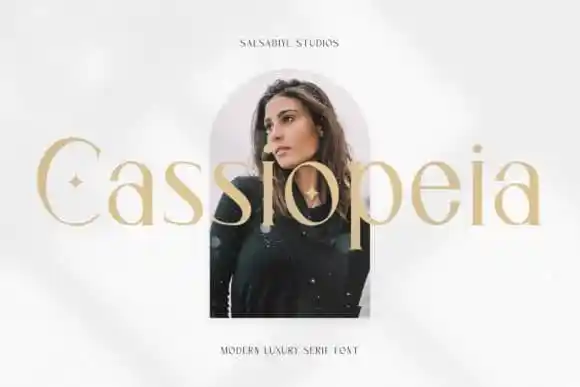
Cassiopeia Serif Font – Download Grátis
A Cassiopeia Serif é uma elegante tipografia serif que traz os benefícios do design moderno, minimalista e moderno ao mesmo tempo. Perfeita para seus projetos de marca pessoal, esta fonte oferece alternativas de caracteres suficientes para atender a um público diversificado. Salsabiylstudios é o criador desta elegante tipografia que abraça o design altamente sofisticado e refinado. Ela se destaca com suporte multilíngue, garantindo facilidade em diversos idiomas. A Cassiopeia é uma escolha ótima para designers de gráficos, seja para criar um logomarca perfeita ou qualquer material de marca ou publicidade. Seja para cartões de visita, cards de presente, camisetas, capas, miniaturas, impressos, panfletos, fotografias, citações ou quaisquer outros projetos gráficos que você possa imaginar. A Cassiopeia é uma escolha sólida e confiável para qualquer designer buscando um estilo limpo e sofisticado.